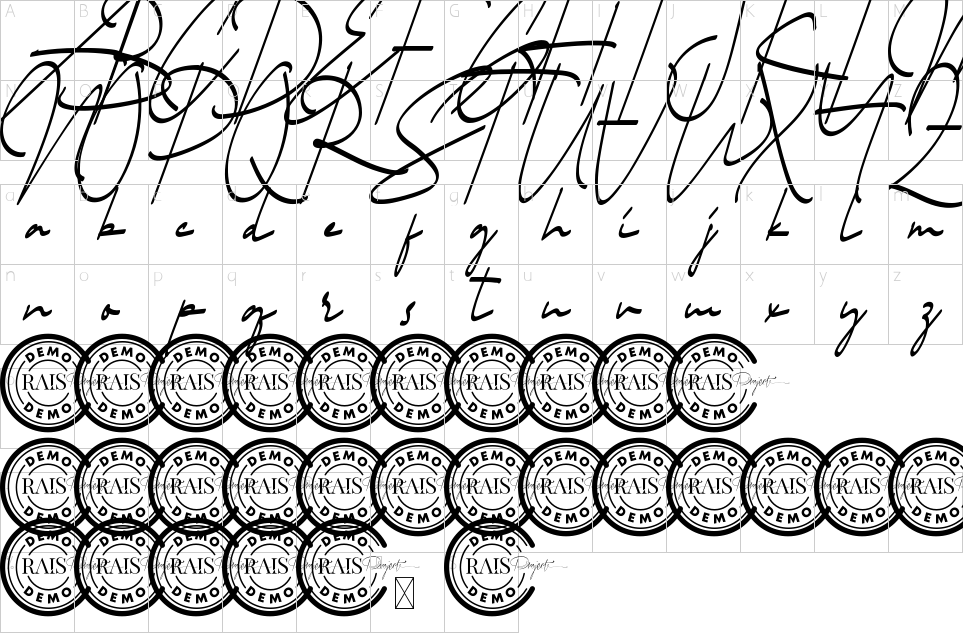
Jaysen é uma fonte de linhas leves e elegantes, perfeita para textos de design gráfico. Seu design contemporâneo faz dele uma opção ideal para projetos que exigem um estilo minimalista e sofisticado. Desenvolvida pelo designer não informado do projeto raisproject, Jaysen foi projetada para acomodar diversos usos, desde logotipos até textos de escrita. A fonte é uma fonte de 1001 Free Fonts, um catálogo de fontes gratuitas que oferece uma ampla gama de opções para profissionais de design gráfico. Foi baixada 2,277 vezes, indicando a sua relevância e popularidade. Seja você um estudante de design ou profissional, encontrarás em Jaysen uma opção de fonte versátil e de alta qualidade.